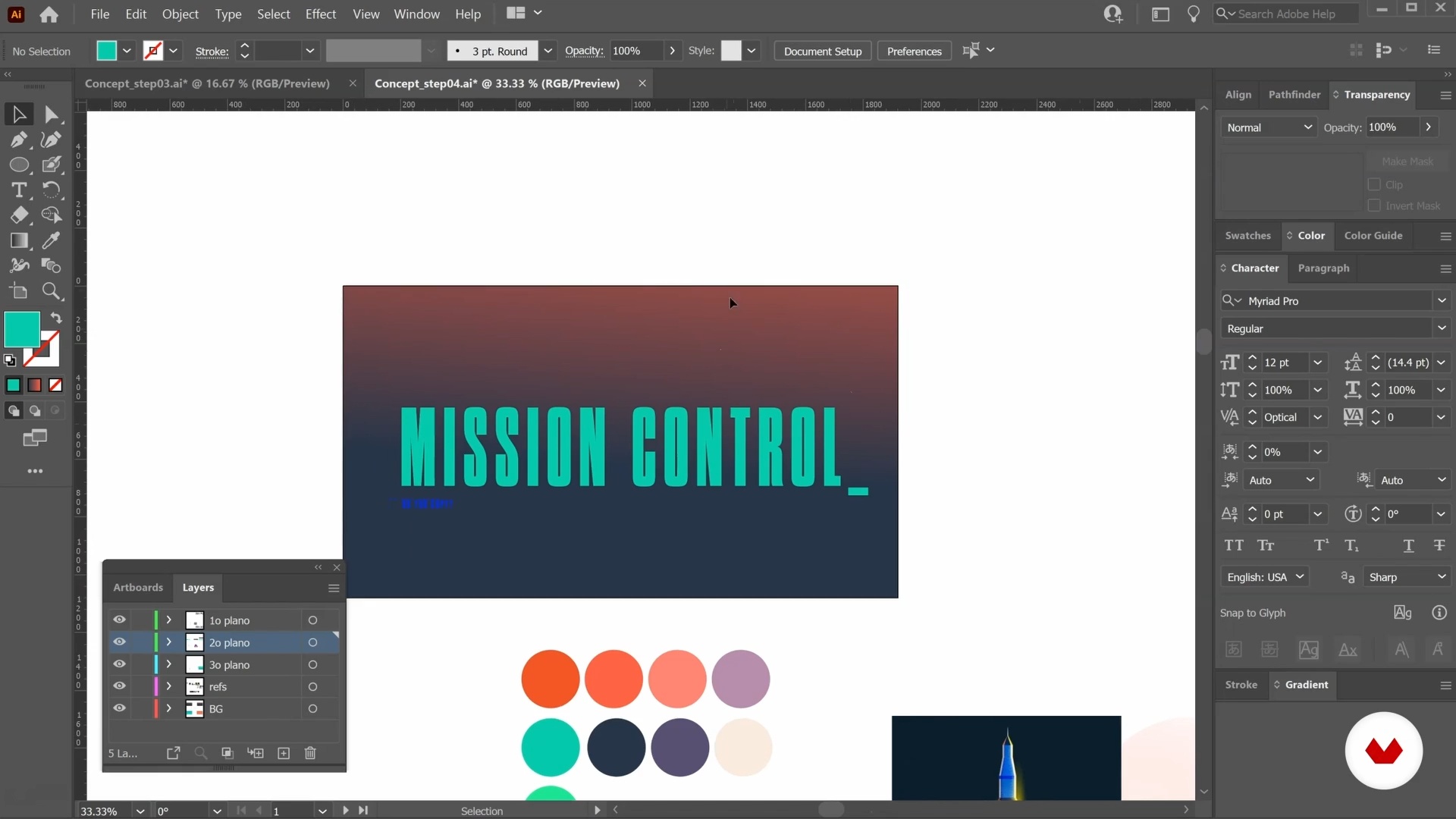
La tipografía como elemento compositivo
Sobre la videolección: La tipografía como elemento compositivo
“Aquí verás que las letras y tipografías van mucho más allá de las simples palabras, siendo un elemento muy versátil para tus composiciones.”
En esta videolección, Daniel Kano aborda el tema: La tipografía como elemento compositivo, que forma parte del curso online de Domestika: Creación de layouts para animación 2D. Aprende a crear una viñeta artística con Illustrator, Photoshop y After Effects y cuenta historias gráficas llenas de emoción y movimiento.
“La tipografía como elemento compositivo Les voy a mostrar ahora que las letras y las fuentes son mucho más que palabras. En realidad, son un elemento versátil para realizar tus composiciones. Además del último documento en el que trabajamos sobre colores, Voy a empezar a trabajar con composiciones de fuentes. Como diseñador, siempre me ha fascinado conocer los nombres de las fuentes de color. Pero aprendí que no se trata de saber los nombres de las fuentes y sí sus características. Es una de las etapas donde más tiempo me tomo porque cada fuente es única y tiene muchas consecuencias. Es una...”